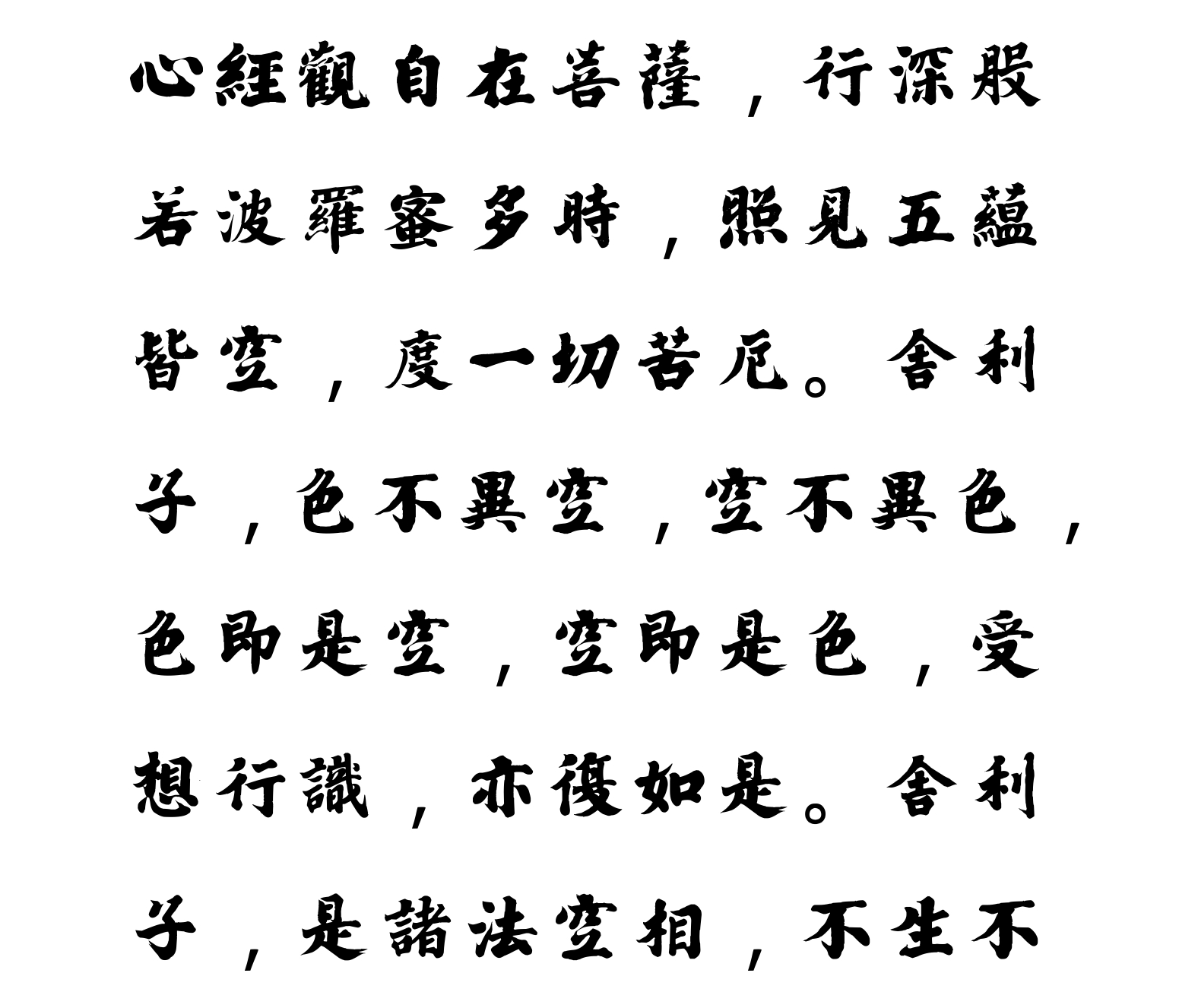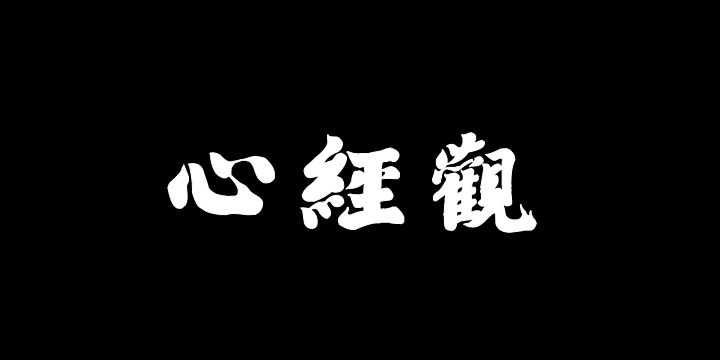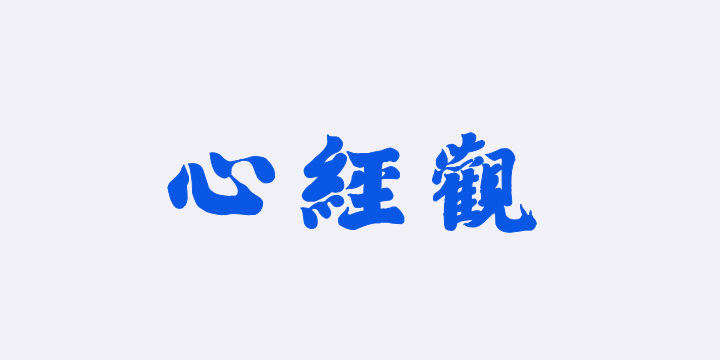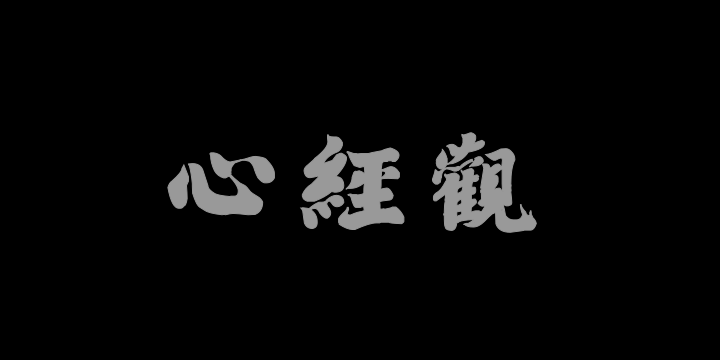
字体全名: 汉标弘法大师心经
字体简介: 1、下载须知:汉标弘法大师心经 字库非标准GB2312字库。本字库只包含了真迹书法原稿中的部分字体。字库中字数的多少取决于原稿的字数的多少。你可以通过该字详情页上面的输入框如果有明白的请先联系字觅客服咨询。 2、简介:本字库由“汉标字库”根据收集到的真迹书法图片,并运用抠图、处理背景图、运用造字软件书法作品调整字体笔画基本位置,合理布局,提高清晰度,去除笔画边缘毛刺及脏点,纠正错别字,均衡整体文字的大小,再次创作而制作成现代字库,再将原版汉字逐字编码代入模板,在制作成小字库。这样做有助于中国古代书法艺术的传承具有划时代意义,并且通过把古代名家书法真迹制作成现代字库,让更多书法爱好者能够通过电脑打字使用,真正感受到古代名家书法之美。并且也可以在各种场景下应用。 3、古代真迹的书法家有:王羲之、王献之、欧阳询、颜真卿、柳公权、赵孟頫、苏轼、黄庭坚、米芾、蔡襄等